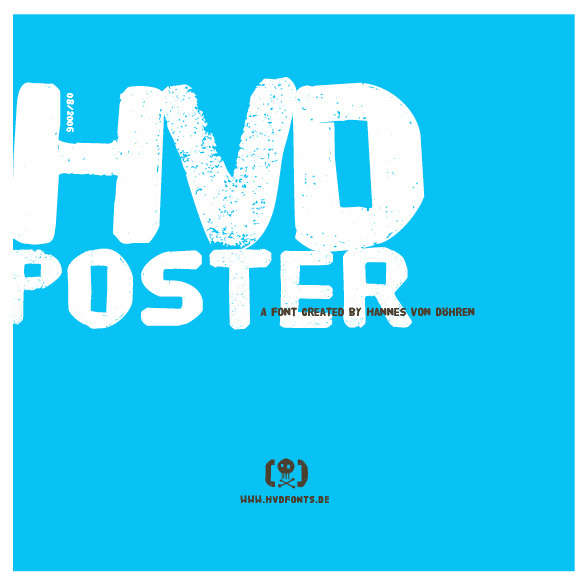
HVD Poster von Hannes Von Döhren ist eine kostenlose, raue Display-Schrift, die aussieht, als wäre sie über Beton gezogen und direkt auf das Papier gestempelt worden. Die massiven, aufrechten Buchstaben mit ihren unebenen, gesprenkelten Innenflächen verleihen jedem Wort einen verwitterten, handgedruckten Look – wie Konzertplakate an einer Ziegelwand oder mit Tinte verschmierte Protestschilder. Die Textur ist markant, aber kontrolliert, sodass Ihre Botschaft auch aus der Entfernung laut und lesbar bleibt.
Mit HVD Poster wirken Schlagzeilen roh, laut und lebendig. Damit eignet sich die Schrift perfekt für Musik-Flyer, Festival-Branding, Zines, Streetwear-Designs, Skateboard-Decks und griffige Social-Media-Promos. Dieses kostenlose Font glänzt in großen Größen, bei denen die körnige Textur voll zur Geltung kommt. Kombinieren Sie es für kleinere Texte mit einer klaren geometrischen Sans-Serif, damit das Layout lesbar bleibt, während die rauen Buchstaben die Aufmerksamkeit auf sich ziehen.